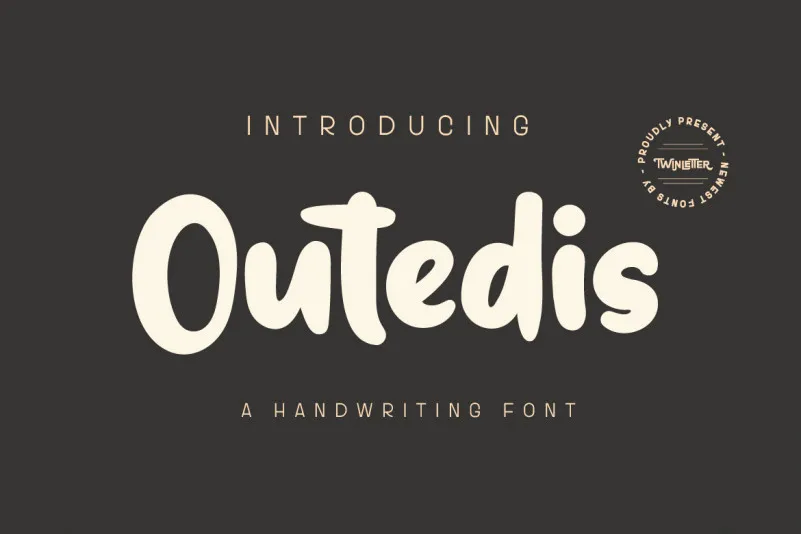
A ‘Outedis Font’ é uma elegante fonte display que destaca-se pela sua personalidade única e encantadora. Criada pelo designer twinletter, ela traz um toque delicado e gracioso a qualquer projeto visual, tornando-a perfeita para desenhos de alta qualidade. Com seu estilo retrô e sua escrita cuidadosamente elaborada, esta fonte é ideal para design gráfico sofisticado, desde identidades corporativas até capas de livros e logotipos de empresas elegantes. Ela traz a graça da letra cursiva ao seu trabalho, sem perder a força e o impacto que um projeto profissional requer. Seja você um designer iniciante ou um profissional experiente, ‘Outedis Font’ é uma ótima escolha para aqueles buscando adicionar um toque único à sua arte digital.